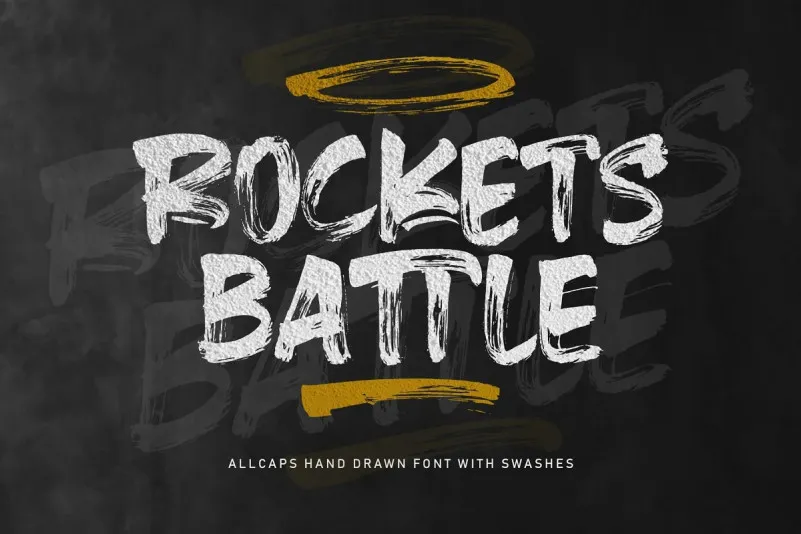
Rockets Battle Font – Download Grátis
A ‘Rockets Battle Font’ é uma elegante letra brush feita com cuidado para capturar os detalhes do pincel, perfeita para criações de logotipo, arte digital de letras, design de signos, marcas e até posts nas redes sociais. Seu estilo criativo e moderno torna-a ideal não só para estilos limpos ou chamativos, mas também para elementos gráficos digitais que exijam uma escrita cheia de personalidade. Com um aspecto atraente e fluido, esta fonte é perfeita para quem busca uma opção única e divertida para enriquecer seu design. Perfect para qualquer projeto em que você esteja procurando algo inovador e visualmente atrativo!